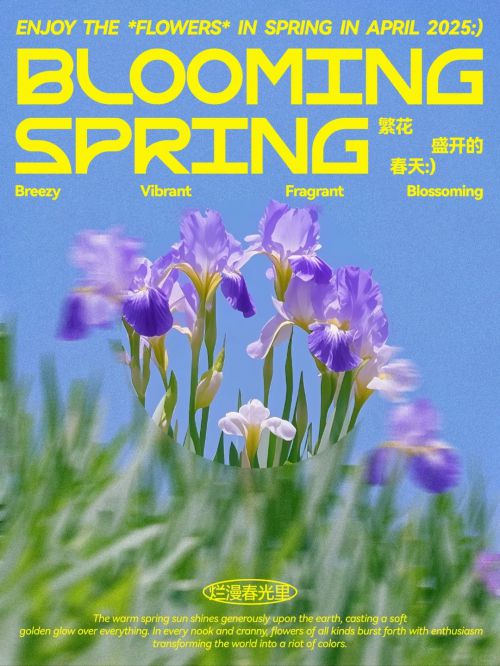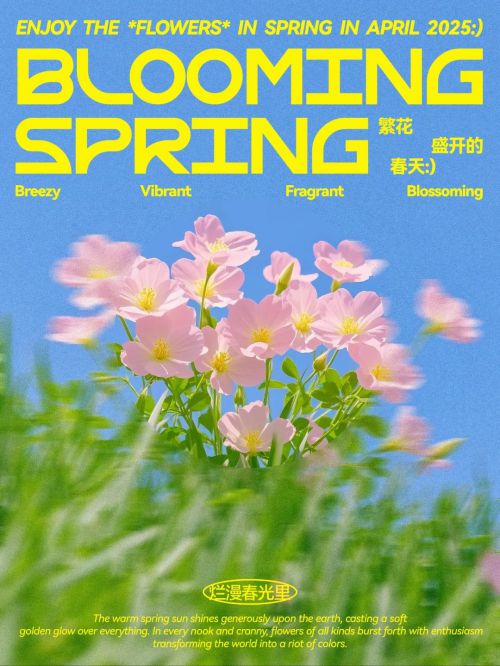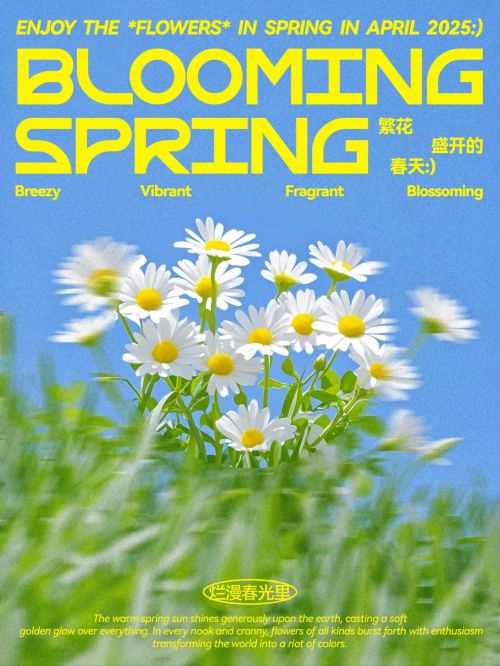
Overt
Overt是一款专为英文设计的现代Display字体,以“有趣/现代”为核心风格,支持免费商用授权,为创意设计项目提供兼具个性与实用性的文字解决方案。 Overt字形修长利落,重心偏高的设计赋予字体向上的轻盈张力,中宫适中的比例则平衡了视觉节奏,让整体形态既保持现代感又不显局促。其笔型设计尤为独特:斜切处理的笔画边缘打破传统直线的沉闷,在方头笔画的硬朗基底上增添灵动弧度;“断开式”笔画连接更成为标志性特征——字母结构中恰到好处的留白与分离,让每个字符都如同独立的设计单元,适合作为标题或视觉焦点文字,轻松吸引观者目光。 作为粗字重字体,Overt粗细均匀的笔画兼具力量感与细腻层次,适配从时尚品牌LOGO、创意海报主视觉到社交媒体标题等多元场景。免费商用的授权范围进一步降低设计成本,让设计师无需担忧版权问题即可大胆应用。无论是追求个性表达的年轻品牌,还是需要现代美学加持的视觉项目,Overt都能以独特的“有趣设计”与“实用属性”,成为提升作品记忆点的理想选择。